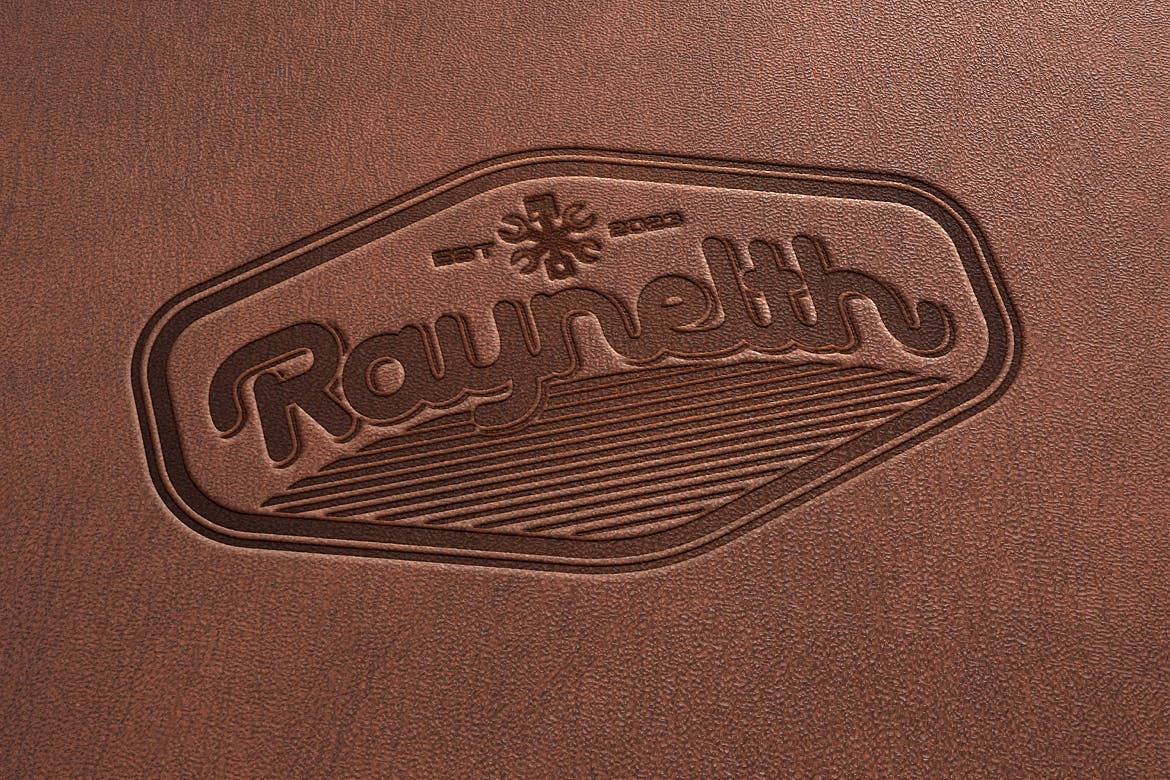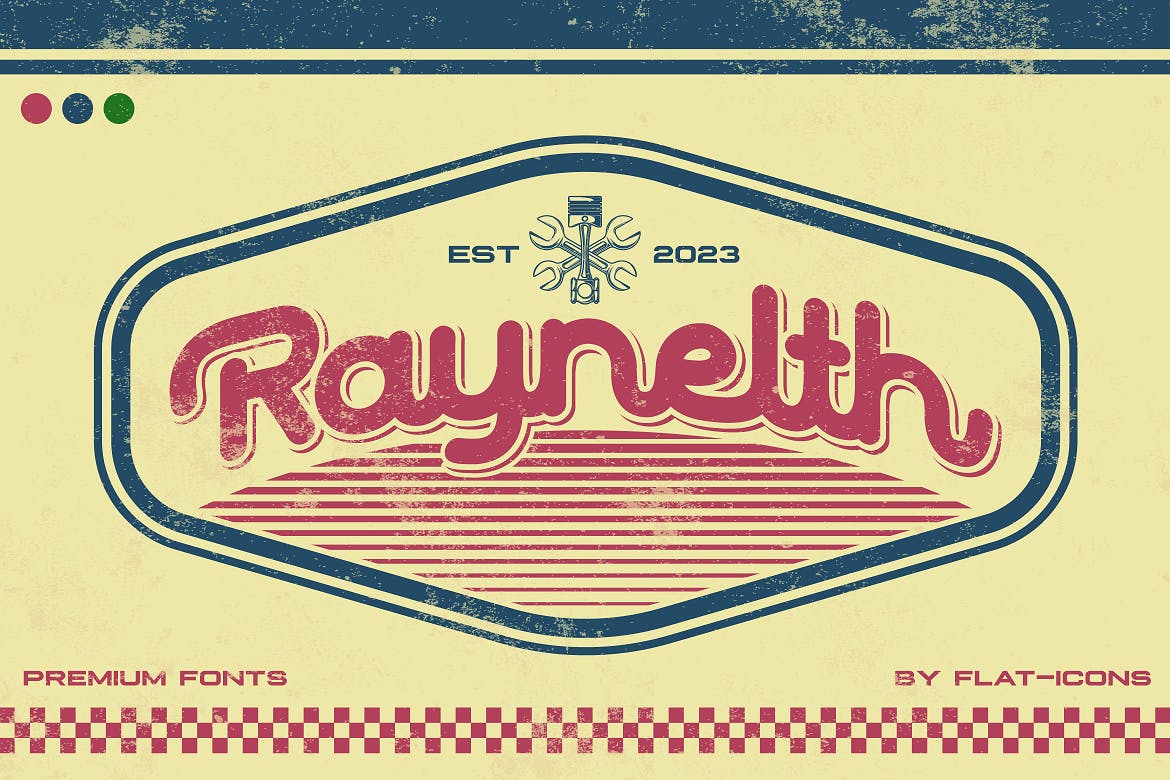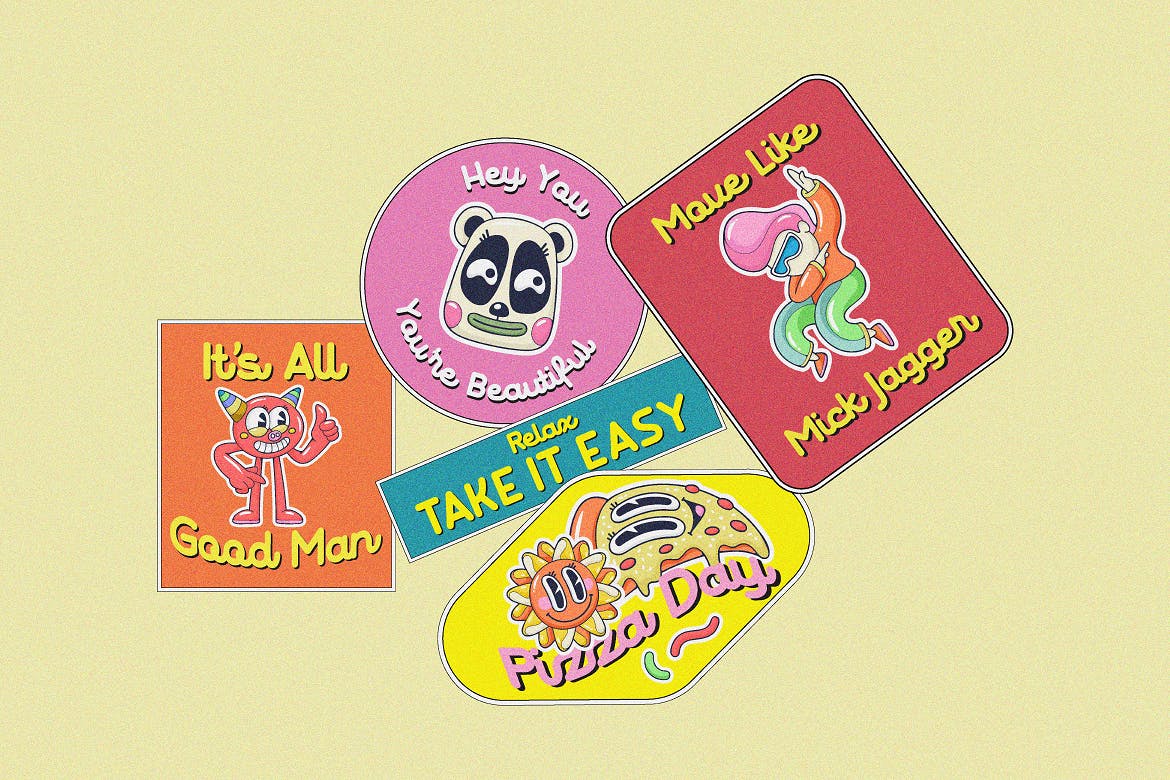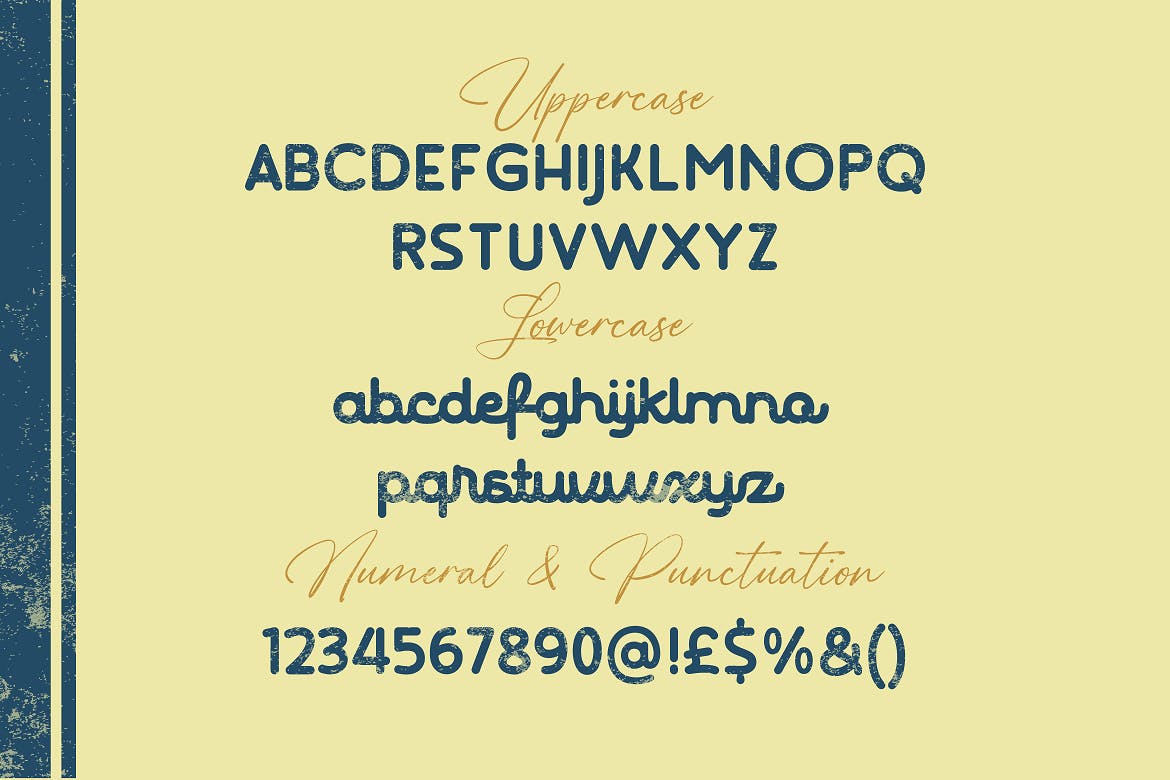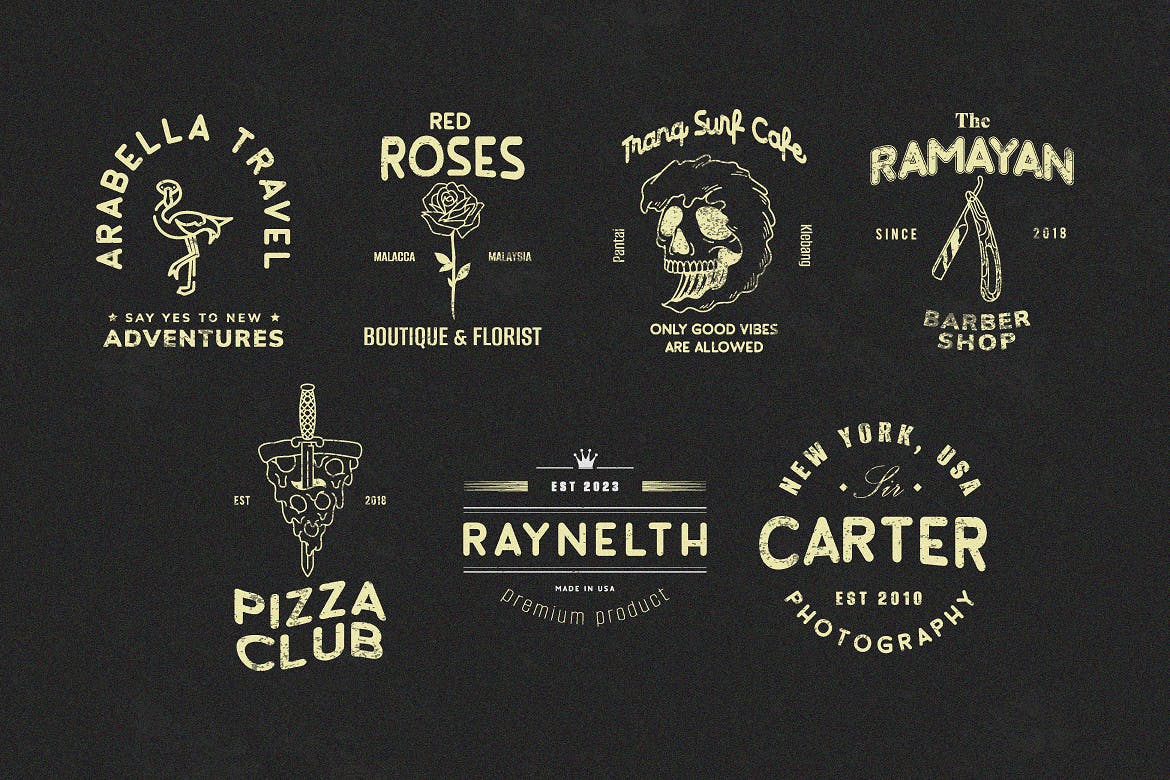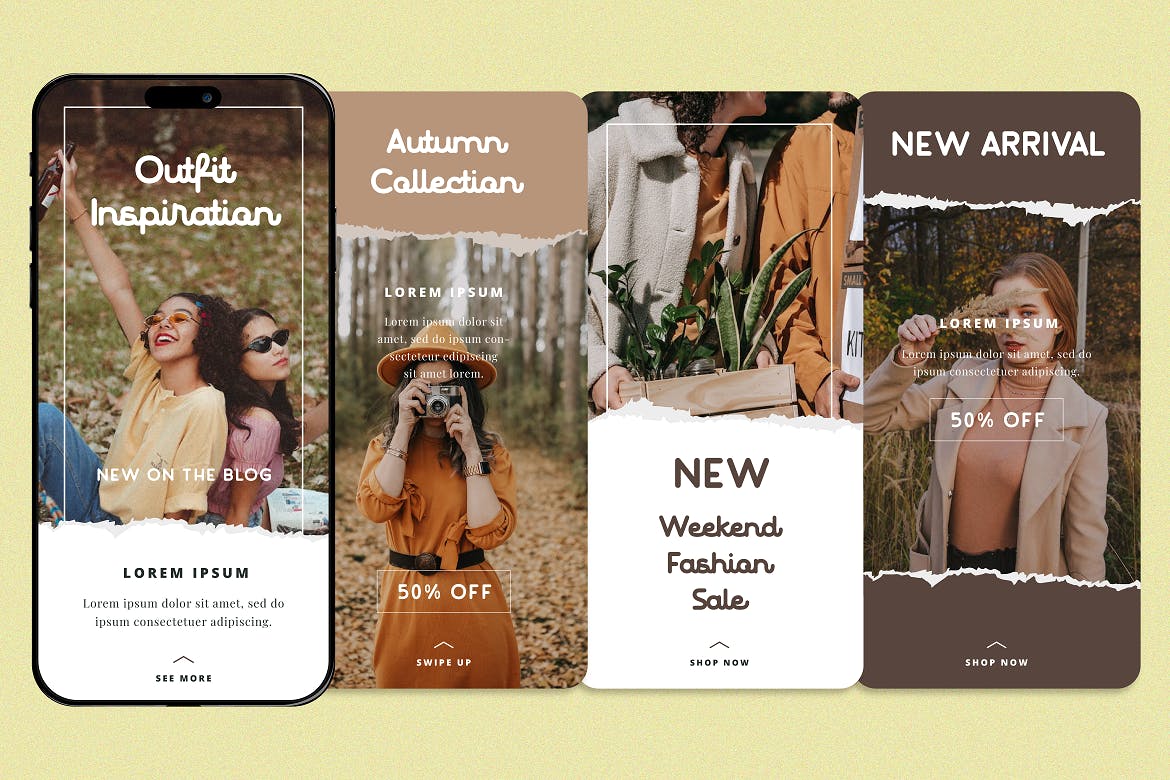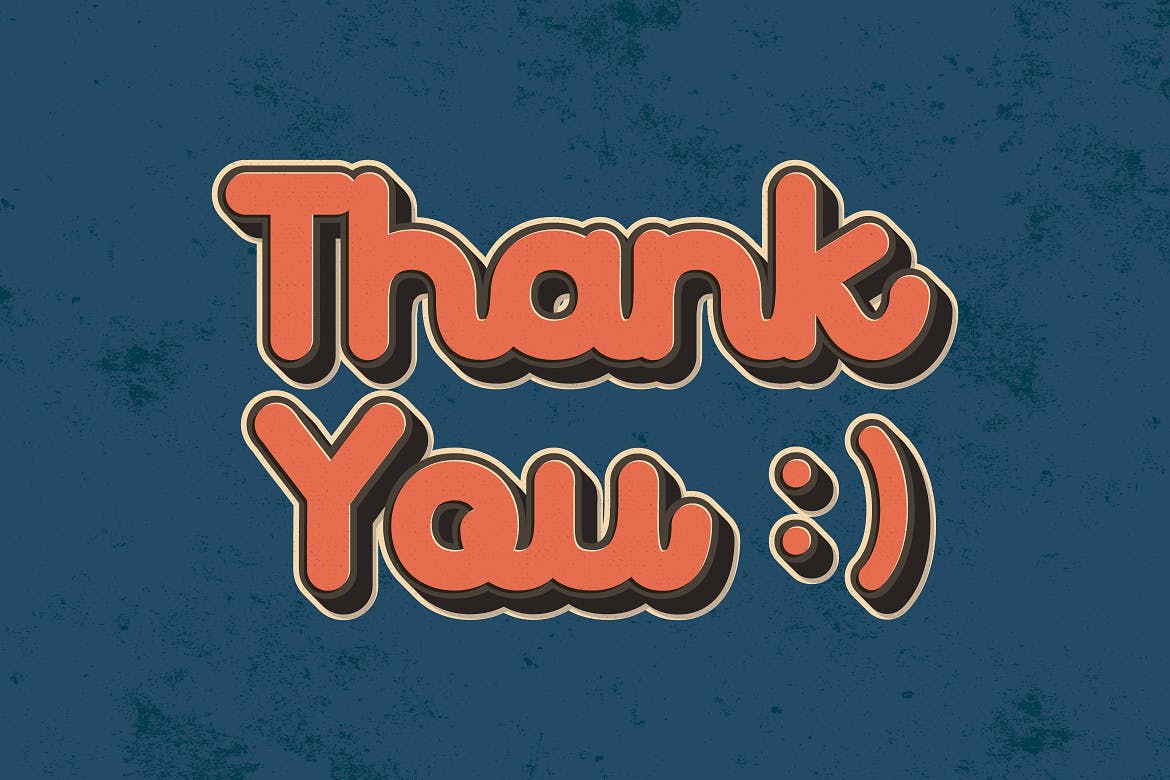
آیا به دنبال افزودن یک لمس فوقالعاده به تصویر برند خود هستید؟ چه شما یک نوآور باشید و چه کلاسیک، ما دقیقاً چیزی داریم که نیاز دارید.
معرفی فونت لوگو رینلت - Raynelth.
از طراحی لوگو گرفته تا رسانههای دیجیتال و چاپی، رینلت یک تأثیر به یاد ماندنی ایجاد میکند. آن را امتحان کنید و از تمام مزایای یک فونت واقعاً جذاب لذت ببرید.